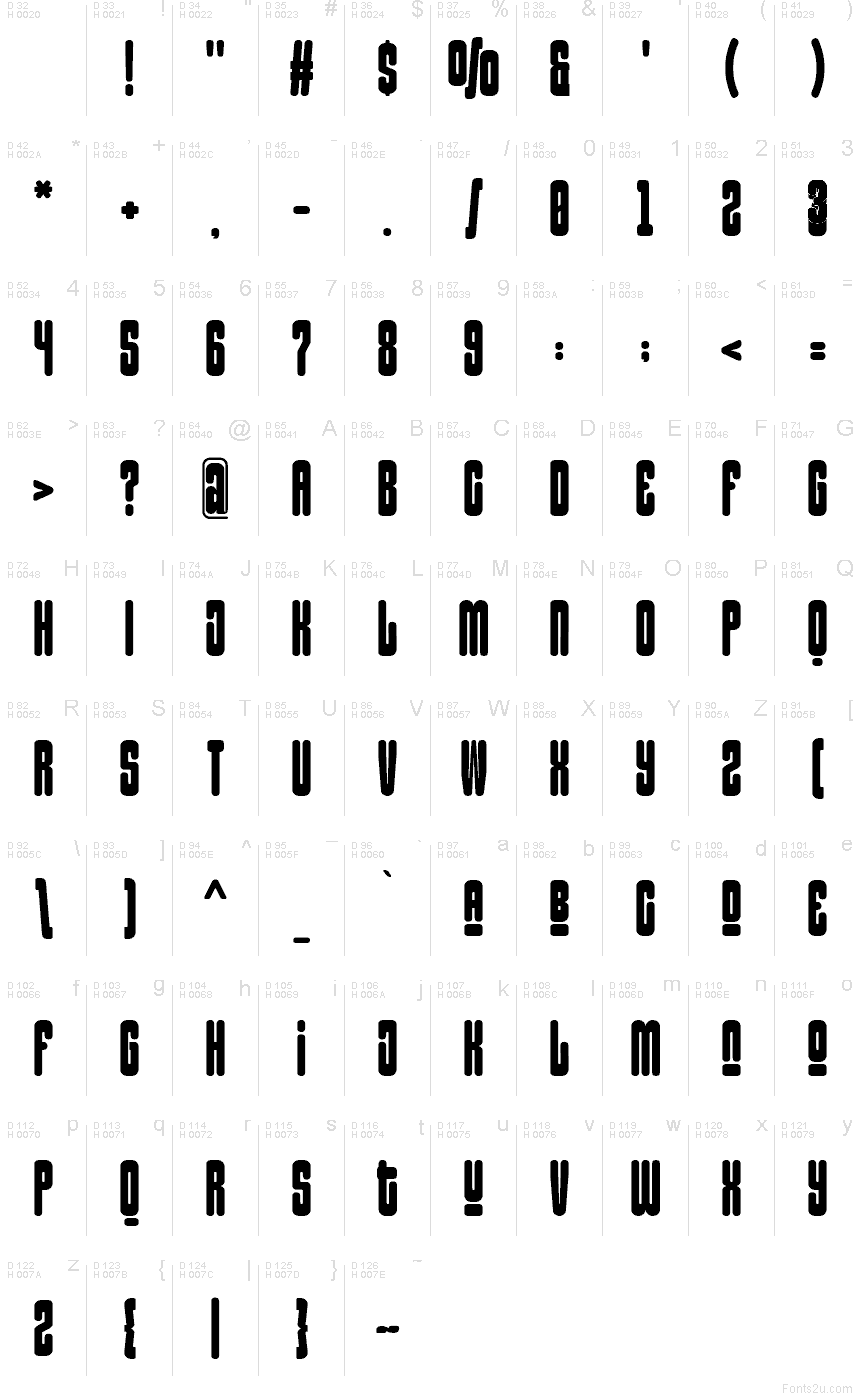
Lifloon, da Linecreative, é uma fonte display gratuita e futurista com um toque retrô, caracterizada por letras extremamente estreitas e traços grossos e arredondados. Pequenas aberturas em forma de fenda cortam as formas densas, e as extremidades suaves dão às letras uma aparência inflada.
Tanto pôsteres musicais quanto embalagens de petiscos podem aproveitar essa combinação de proporções compactas e curvas volumosas para sugerir algo marcante e divertido. Em produtos promocionais, as letras têm um peso visual semelhante ao de ilustrações encorpadas de desenho animado, com cantos arredondados que ecoam os contornos simples e inflados da arte.